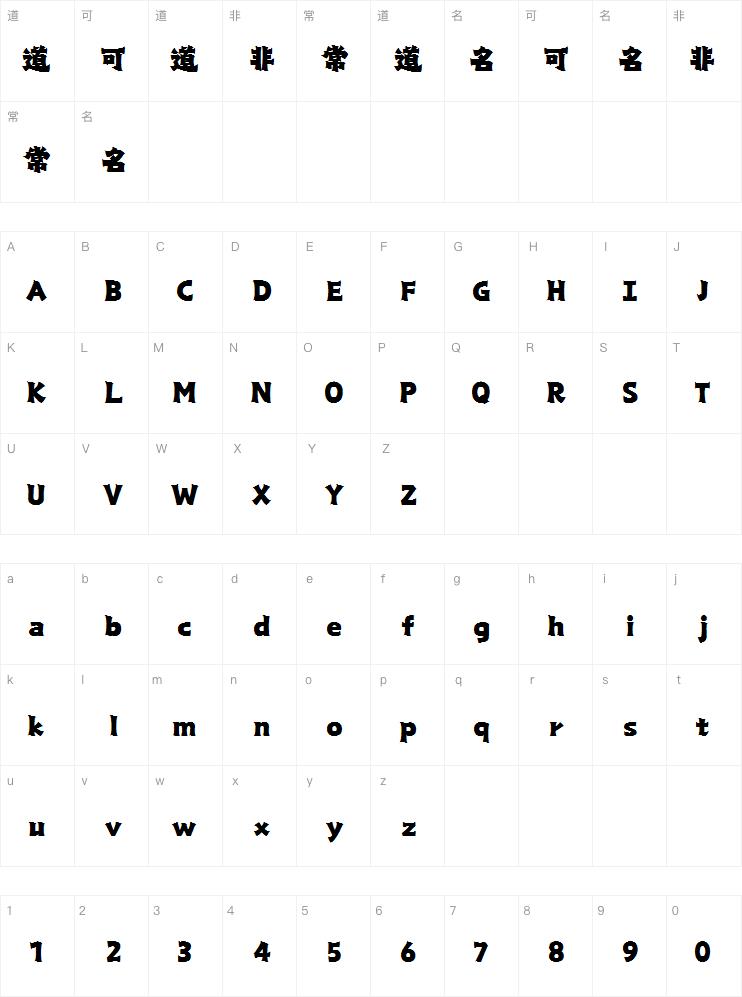
山海魏碑劲榜,是一款全新魏碑风格的字体,包含汉字9169个,符号200+个。该字体是一款具有强劲视觉冲击力的魏碑风格的字体。字形结构多为方形结构,如正方形、长方形或扁方形,强调字形的稳定性和内敛精神。字形大小悬殊,通过大小不一的字来形成对比和层次感,造型硬朗,直线与曲线结合的笔画构成棱角分明、坚实有力。